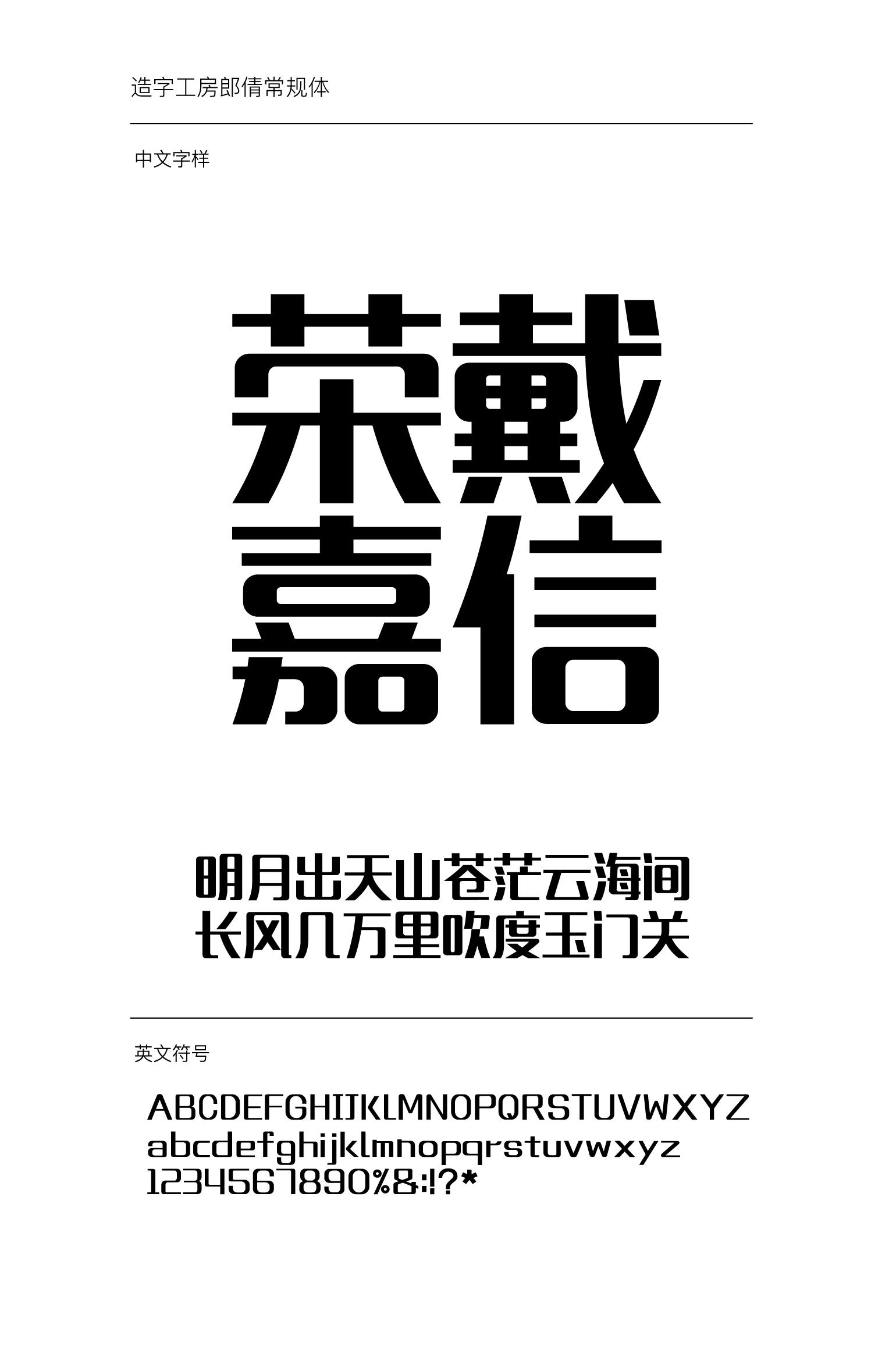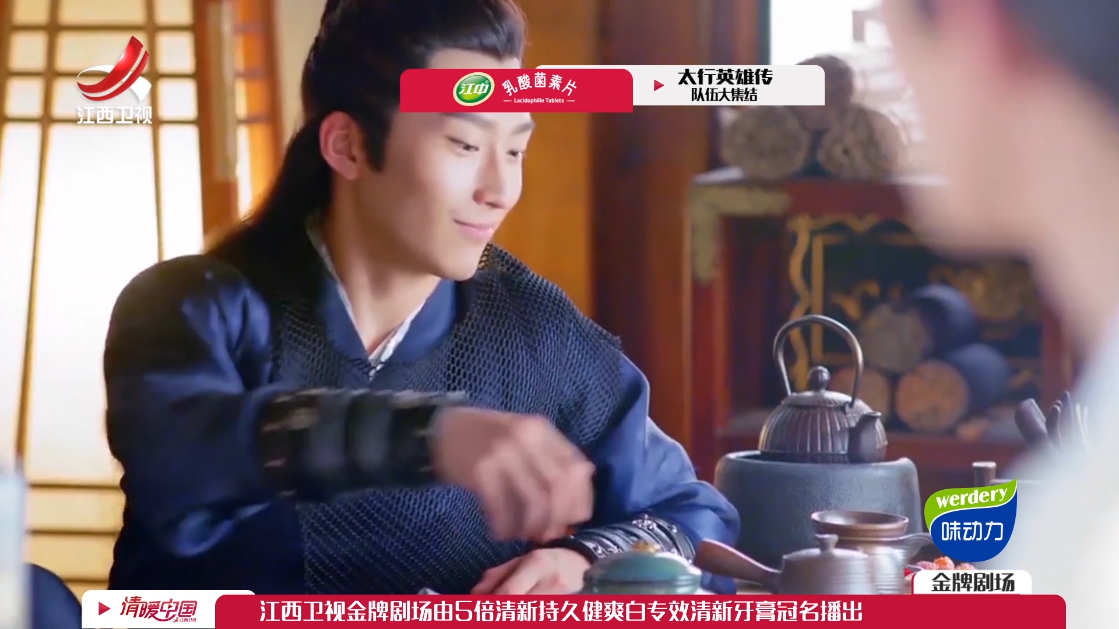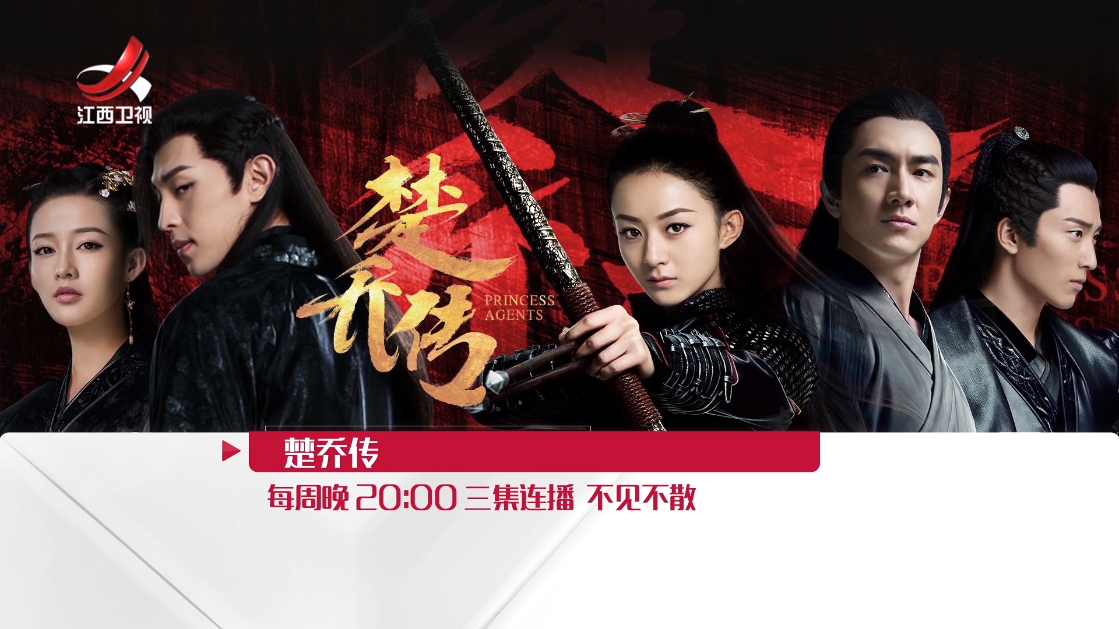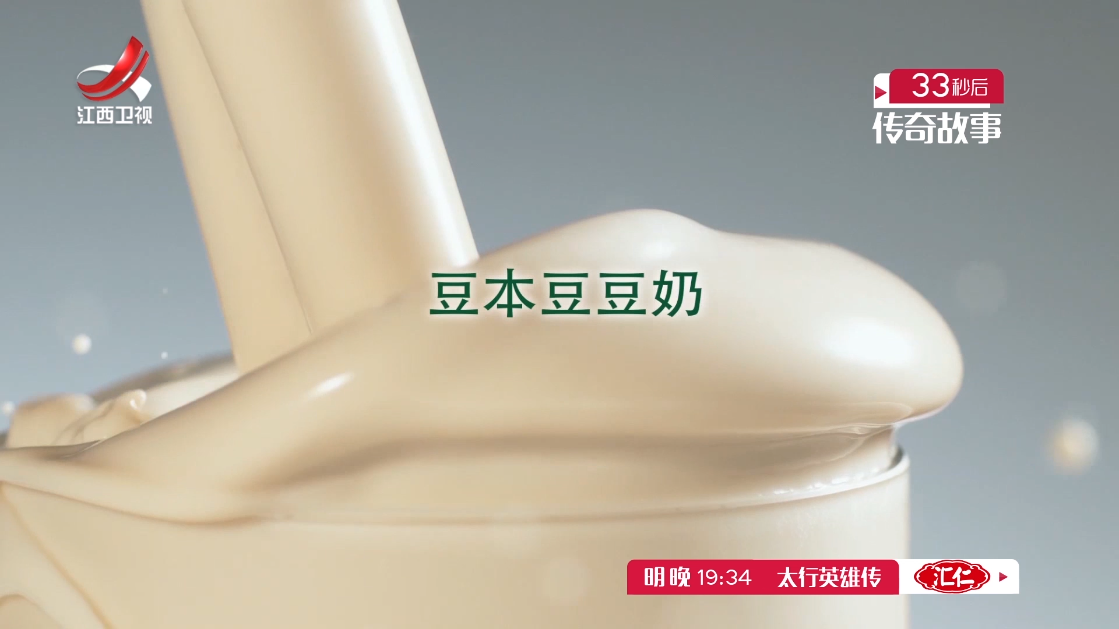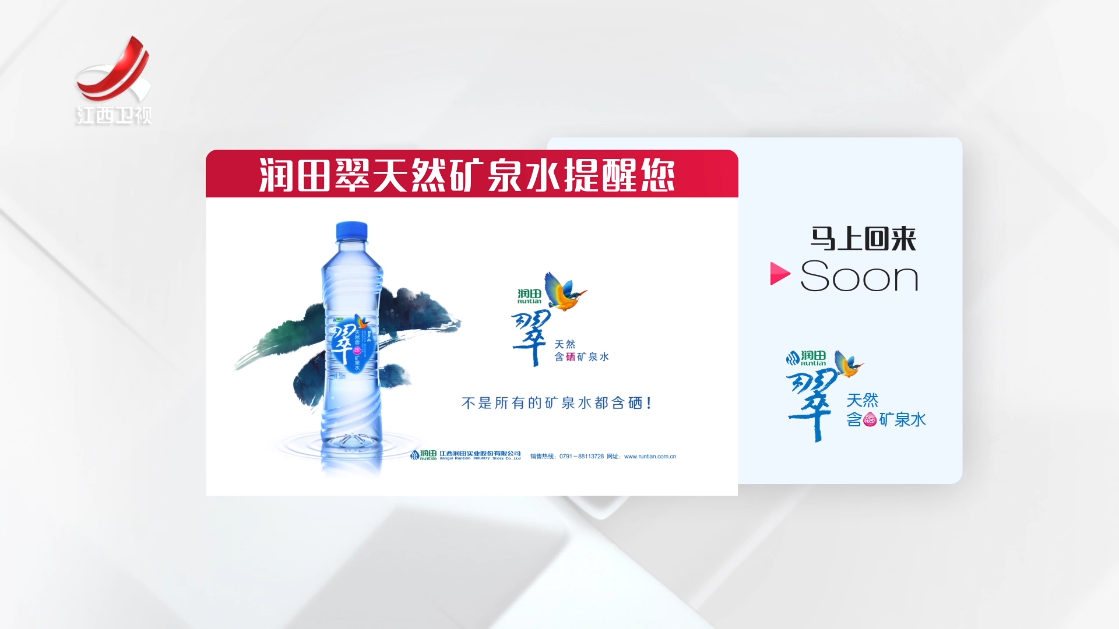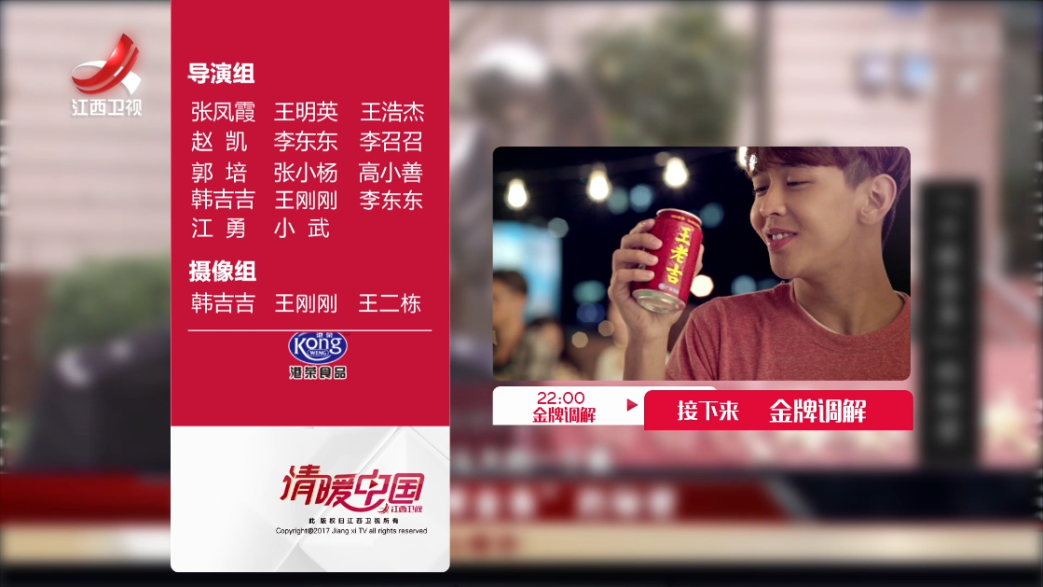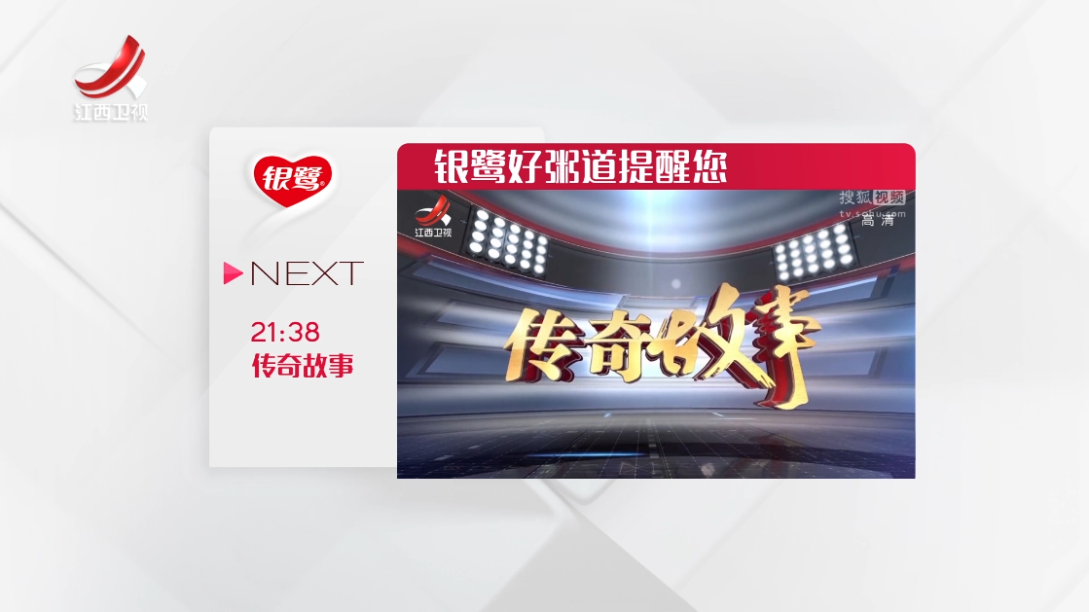
造字工房朗倩亮相江西卫视 全新导视系统简约时尚
3月3日,江西卫视全新导视系统上屏,在设计上,卫视频道追求简约、时尚的设计风格,个性化表达,突出江西卫视独特的品牌气质。
色彩以红色、白色为主色,与台标色相对应,颜色干净清晰;动画强调节奏韵律;卫视频道经过反复对比,最终选取造字工房朗倩字体作为频道导视的主字体,字体清晰,简洁时尚。
基于以上几个方面,呈现出不一样新导视系统,新的导视系统使得播出内容变得更加灵活,栏目之间的过渡变得更加顺畅,屏幕画面效果更好,给观众全新的视听感受。
造字工房朗倩常规体设计说明
造字工房朗倩体共三款,笔画简洁、粗细分明,中正不失圆润,曲线流畅,结构稳重大方,整套字形柔和饱满,如玉似珠,为汉字灌注了无限生机。整体字形姿态横生,结构疏朗飘逸,字里行间蕴藏一种闲适沉静之美。
造字工房朗倩共3款:常规、细体、粗体